说到霓虹灯相信不少人也跟我一样第一个想到的是香港电影里炫彩斑斓的霓虹街景。霓虹灯沉浸式香港最具有代表性的视觉符号,在王家卫等导演的许多电影中都能看见它的身影。霓虹灯是城市的美容师,每当夜幕降临时,华灯初上,五颜六色的霓虹灯就把城市装扮得格外美丽。现在霓虹灯蒸汽波这种复古特效也非常受设计师的欢迎,今天小编要跟大家分享两款可适用于霓虹灯风格的字体,一起看下面字体图片吧。
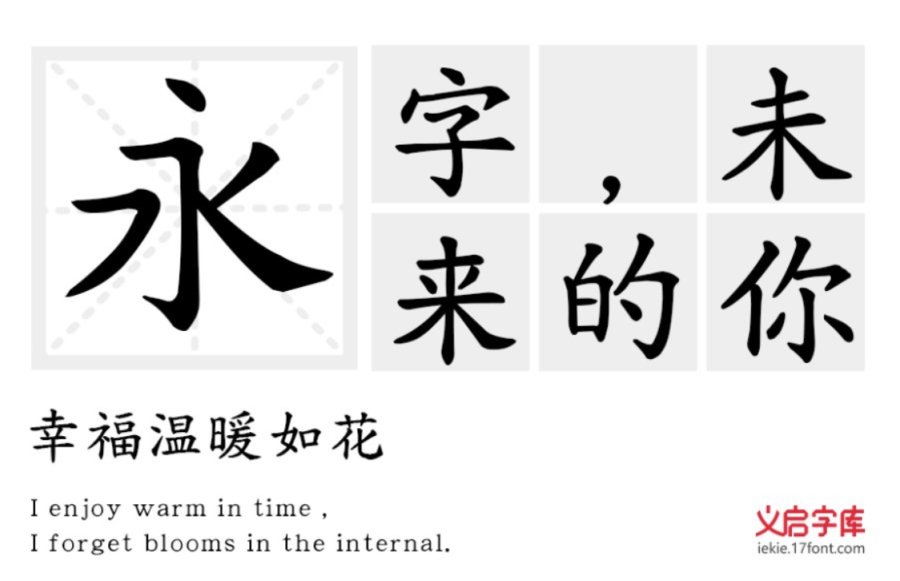
义启粗楷体:这款大量吸取了唐楷的元素,不但笔画上浑厚有力,机构上也收放夸而不张。整个字变的生动活泼起来,而字与字之间也遥相呼应,整体读来一气呵成。无论线条、结构还是章法都使得粗楷独树一帜。
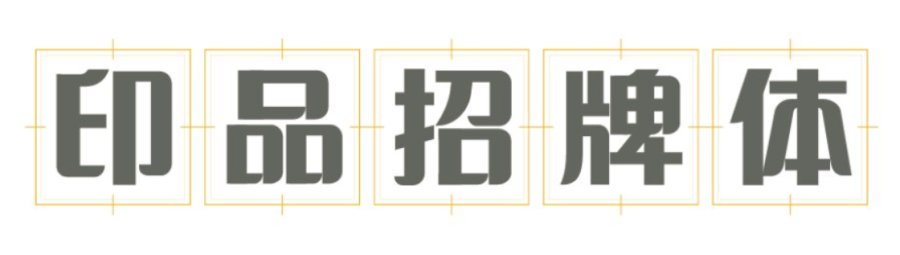
印品招牌体:这款招牌体字整体方正笔画粗壮,略带有纤细笔触,字形紧聚,但不失美感。在弯钩处都作了一点线条处理,看起来不那么死板。它的一撇一捺像极了柳絮飘飘。不会产生视觉突兀,给人以浑厚有力的感受 。